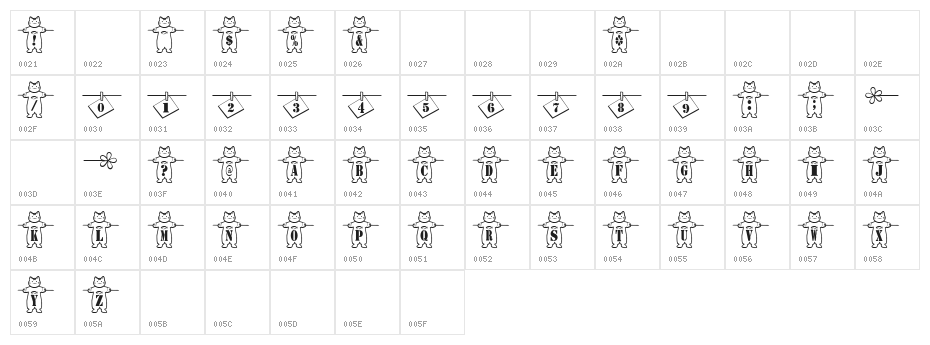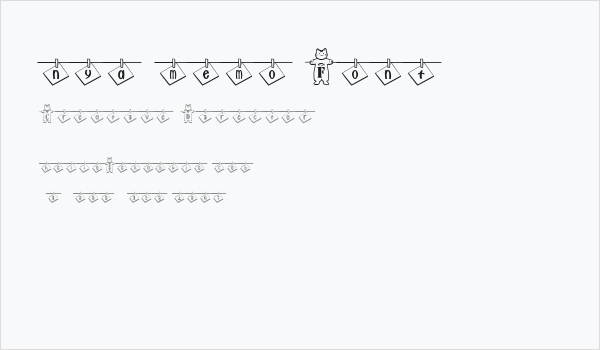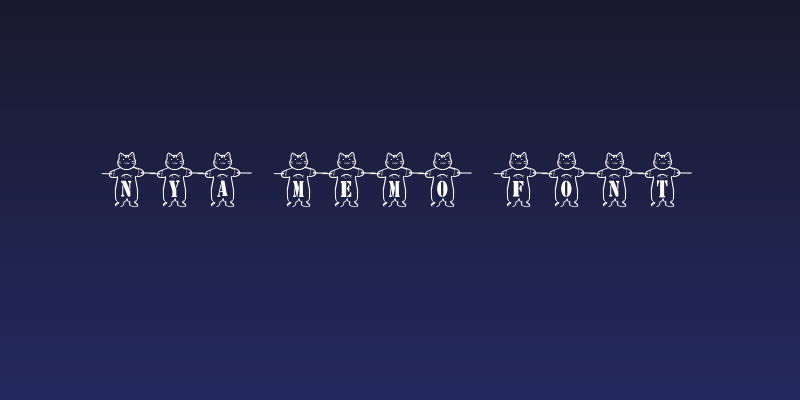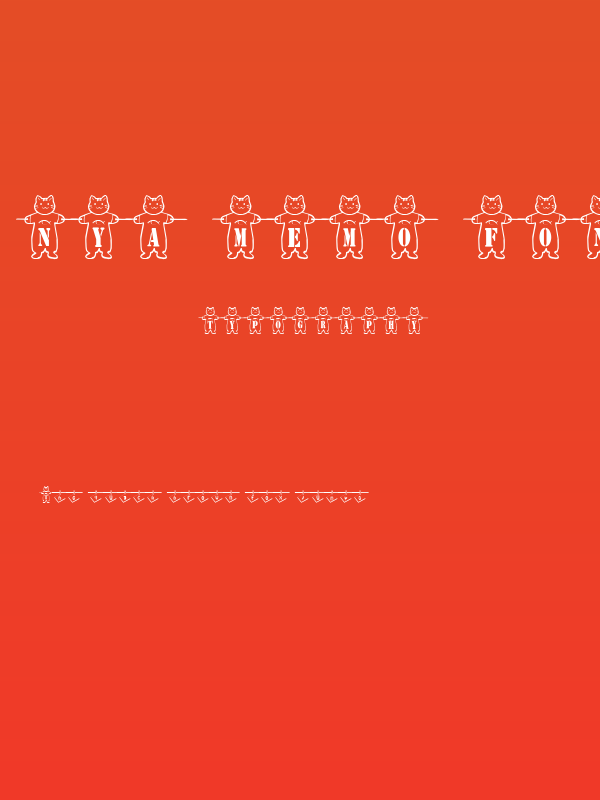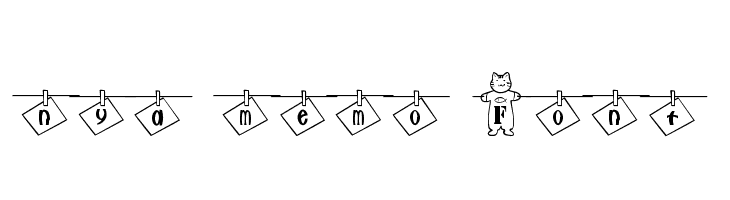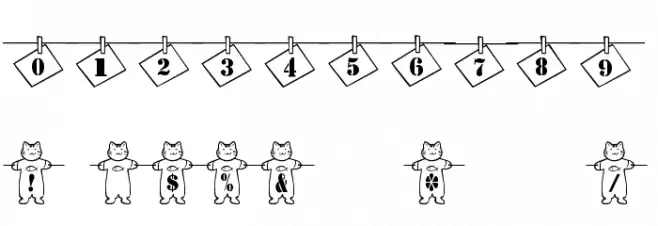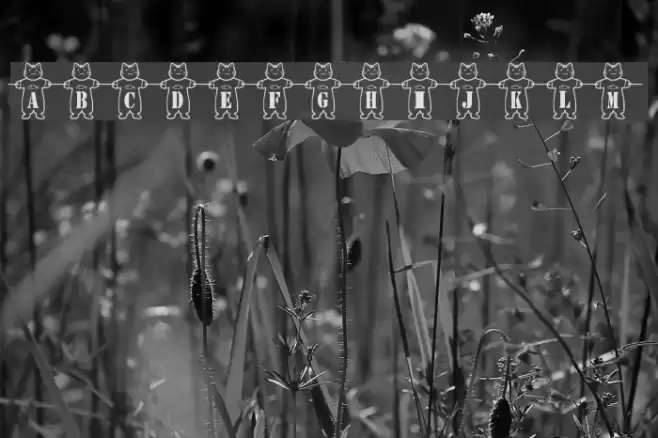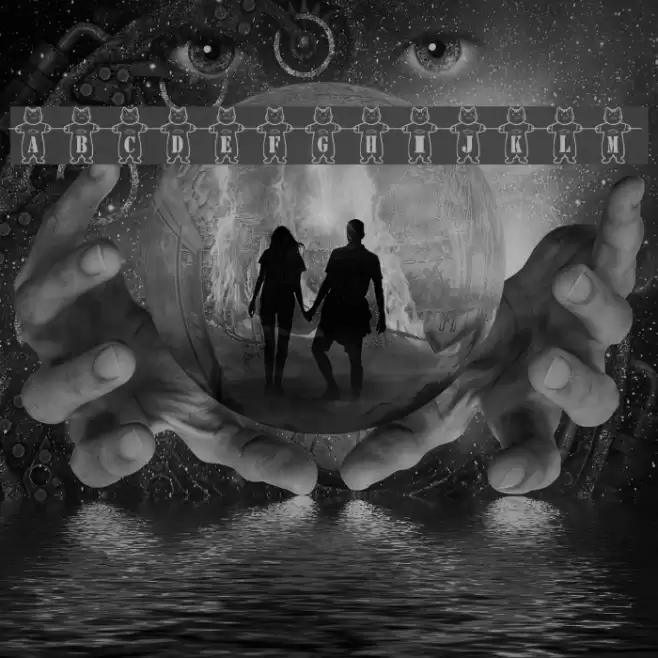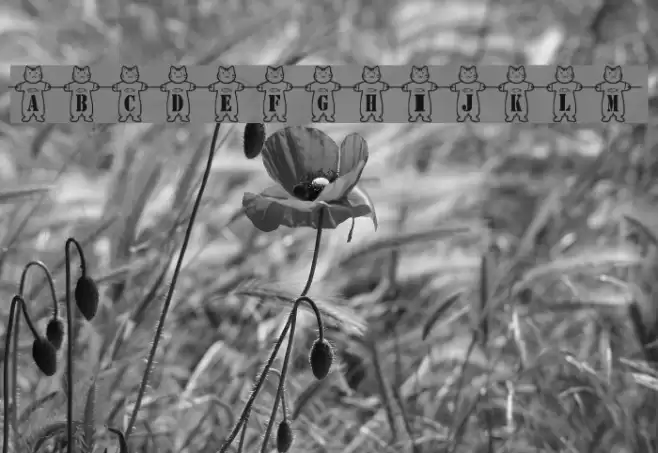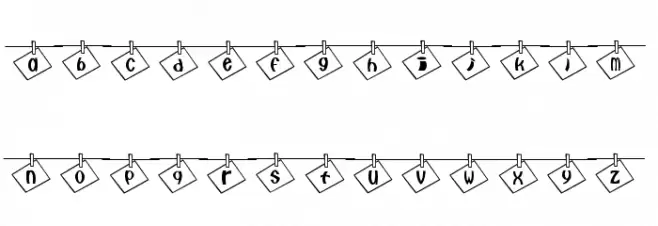
nya-memo Font Font
| Anwendungsfall | Headlines, Logos, Decorative Text |
| Vorgeschlagene Projekte | Ideal for children's books, playful branding, greeting cards, and any project that benefits from a whimsical and fun aesthetic. |